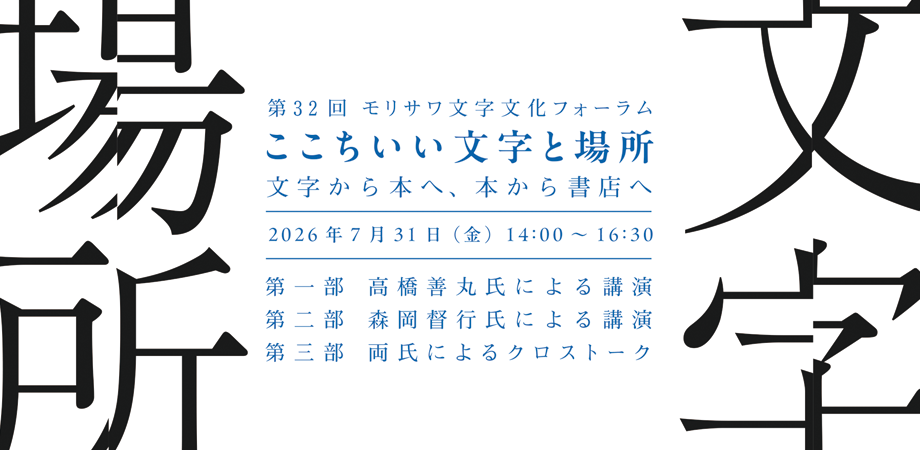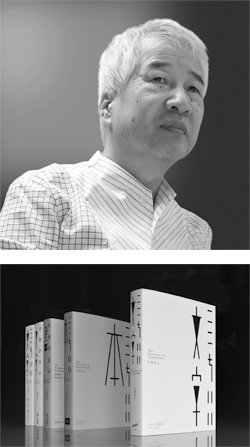
高橋善丸氏と森岡督行氏が登壇 第32回モリサワ文字文化フォーラム「ここちいい文字と場所 ─文字から本へ、本から書店へ」を開催【7/31・大阪】
「モリサワ文字文化フォーラム」は、第一線で活躍するデザイナーやクリエイターをお招きし、文字とデザインの融合から生まれる創造性、独創性、そして表現の可能性を探求することで、文字文化の継承と発展に寄与することを目的に開催しています。
第32回を迎える今回のフォーラムでは、タイポグラフィを主軸としながら湿度ある視覚コミュニケーション表現を探究するグラフィックデザイナーの高橋善丸氏、「1冊の本を売る書店」をコンセプトにした「森岡書店 銀座店」の代表、文筆家でもある森岡督行氏をお招きし、ご講演いただきます。
講演者
高橋善丸(たかはし よしまる) 株式会社広告丸 主宰
森岡督行(もりおか よしゆき) 森岡書店 代表
タイトル:第32回モリサワ文字文化フォーラム「ここちいい文字と場所 ─文字から本へ、本から書店へ」
講演概要
高橋善丸氏の“ここちいい”エモーショナルタイポグラフィ、森岡督行氏が設計する「1冊の本を売る書店」は“ここに行きたくなる”書店。
文字の“ここちよさ”は、書体そのものだけでなく、紙・余白・空間・時間との関係の中で生まれます。表情豊かで五感に“ここちいい”感覚をもってもらえるロゴタイプや書体、本のデザイン、そして、本や空間を使ったコミュニケーションがもたらす“ここちいい”場の可能性についてご講演いただきます。
講演者プロフィール
高橋善丸
グラフィックデザイナー
富山県生まれ。V.Iからブックデザインまで、タイポグラフィを主軸としながら、湿度ある視覚コミュニケーション表現を探究。欧米からアジアまで、講演、審査員、企画展等に多数参画。主な著書に、『ここちいい文字』『ここちいい本』(パイ インターナショナル)、『曖昧なコミュニケーション』(ハンブルク美術工芸博物館)、『高橋善丸設計世界』(中国広西美術出版社)、『くすりとほほえむ元気の素』『レトロな印刷物ご家族の博物紙』『箱中天』(光村推古書院)、『お薬グラフィティ』光琳社出版、他がある。主な受賞に、ニューヨークADC銀賞、特別賞、ニューヨークフェスティバル銅賞、香港デザインアワードGDA銀賞、日本タイポグラフィ年鑑ベストワーク賞、他がある。チューリッヒデザイン美術館、ハンブルク美術工芸博物館、オッフェンバッハキングスポア美術館、パリ広告美術館、大阪中之島美術館、富山県立美術館、他国内外の美術館に作品が収蔵されている。
株式会社広告丸主宰。大阪芸術大学デザイン学科長・教授。中国寧波大学客座教授。日本タイポグラフィ協会理事長。JAGDA、東京TDC、ニューヨークTDC、DAS、各会員。
森岡督行
森岡書店 代表
「文字とデザイン」から生まれる創造性や独創性、創作や表現活動について、より多くの皆様に触れていただく機会として、2010年より不定期に開催しています。モリサワは本フォーラムを通じて、文字の持つ魅力や価値に焦点をあて、ジャンルにとらわれない新しいクリエイティブの探求と、文字文化の継承発展を目指しています。